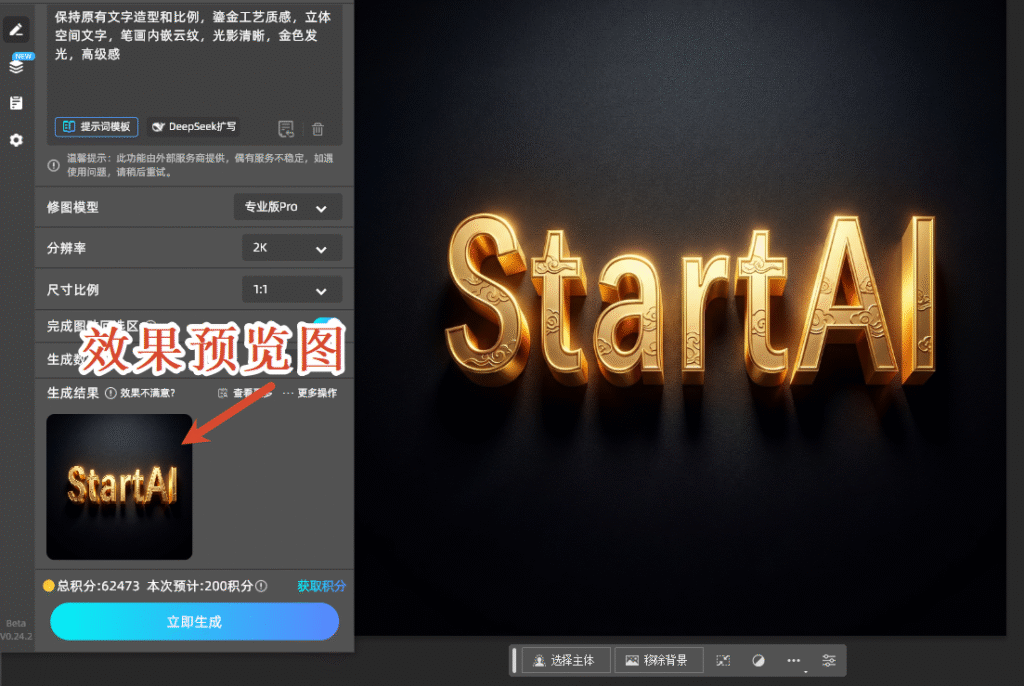
PS字体怎么做出立体感?2种方法新手也能做专业立体字
在Photoshop(简称PS)设计中,立体字体是提升作品视觉冲击力的核心技巧,广泛应用于海报设计、logo制作、电商主图、公众号封面等场景,既能让文字摆脱扁平感,又能增强画面层次感与高级感。很多新手疑惑ps字体怎么做出立体感,其实无论是纯PS原生操作,还是借助AI插件辅助,都有清晰可落地的方法,下面结合实操步骤,详细讲解两种主流方式,兼顾专业性与实用性,新手也能快速上手,同时分享ps立体字体制作的实用技巧,帮助大家高效出片。
一、PS原生操作:图层样式打造立体字体
PS原生操作无需借助任何插件,通过自带的图层样式,就能做出自然逼真的立体效果,适合所有PS版本(包括CC2015及以上),也是ps立体字体制作的基础方法,新手可先从这种方式入手,熟练掌握后再尝试进阶玩法。以下是详细实操步骤,全程无复杂操作,配合参数建议,避免反复调试。
1. 前期准备:奠定立体基础
打开PS软件,新建画布(建议尺寸1920×1080,适配大多数设计场景,可根据实际需求调整),背景色可选择纯色、渐变或纹理,建议背景与文字颜色有明显反差,更能凸显立体效果。
新建画布
选择「横排文字工具」(快捷键T),输入需要制作立体效果的文字,字体优先选择粗体(如思源黑体、Impact、阿里巴巴普惠体),粗体更易呈现立体厚度,避免选择过细字体,否则立体效果不明显——这也是ps字体立体感不突出的常见解决技巧之一。
输入文字后,调整字体大小、位置,确保文字在画布中居中或符合设计布局,选中文字图层,准备添加图层样式。
2. 核心操作:图层样式参数设置
选中文字图层,双击图层空白处,弹出「图层样式」面板,重点设置5个核心选项(斜面和浮雕、投影、内阴影、渐变叠加、描边),这是ps字体做出立体感的关键,每个参数都有明确的作用,可根据文字大小和设计需求微调,以下是通用适配参数,新手可直接套用。
图层样式面板
(1)斜面和浮雕:打造立体厚度
斜面和浮雕是立体字体的核心,主要作用是模拟文字的凸起或凹陷效果,营造基础厚度。
参数设置如下:样式选择「内斜面」,方法选择「平滑」,深度120%(可根据文字大小调整,文字越大,深度可适当增加),方向「上」,大小8-15像素,柔化1-3像素,高度60°,光泽等高线默认即可。
斜面和浮雕参数
小技巧:点击等高线图标,可切换不同高光分布,让立体字的边缘更有质感,这是提升ps立体字体高级感的小细节,很多新手容易忽略。
(2)投影:增强空间感
投影能让文字“站起来”,摆脱画布的扁平感,模拟真实光影下的阴影效果,让立体感更自然。
参数设置:混合模式选「正片叠底」,颜色选黑色或深灰色,不透明度30%-40%(避免过浓显得脏,过淡无效果),角度120°(模拟左上光源,符合人眼视觉习惯),距离12-20像素,扩展0,大小10-20像素。
投影参数
(3)内阴影:提升真实度
内阴影可让文字边缘产生内凹感,像雕刻进去一样,与投影搭配使用,能让立体字的空间感翻倍。
参数设置:混合模式「正片叠底」,颜色选深灰或深蓝,不透明度25%-35%,角度120°(与投影角度一致,保证光源统一),距离4-8像素,阻塞0,大小6-12像素。
内阴影参数
(4)渐变叠加:丰富光影层次
单纯的纯色文字立体效果较单调,渐变叠加能让文字呈现自然的光影过渡,避免死板。
参数设置:混合模式「正常」,不透明度100%,渐变选择同色系浅深搭配(如浅蓝→深蓝、浅灰→深灰,新手最稳妥的选择),样式「线性」,角度90°或120°,比例100%。
渐变叠加参数
(5)描边:强化边缘质感
描边能让立体字的边缘更清晰、更挺括,避免立体效果模糊。
参数设置:大小2-4像素,位置「外部」,颜色选深色或与渐变呼应的颜色,新手可直接选文字本身的深色系,避免颜色过于跳跃,描边不用太粗,否则会掩盖立体字的厚度。
描边参数
3. 细节优化:让立体效果更精致
完成上述图层样式设置后,可进行简单细节优化:选中文字图层,按Ctrl+J复制图层,隐藏复制图层的图层样式,将文字颜色调整为浅色(与渐变叠加的浅色一致),轻微移动2-3像素,作为立体字的高光,进一步增强层次感;
若想让立体字更有质感,可添加「图案叠加」,选择纹理素材,模拟金属、石材等材质,这也是ps立体字体进阶制作的常用技巧。
此外,若需要批量制作立体字,可右键文字图层,点击「复制图层样式」,再粘贴到新的文字图层,一键套用,节省时间,适合电商主图批量制作、海报批量排版等场景——这也是ps批量制作立体字体的高效方法。
二、高效进阶:StartAI插件制作立体字体(省时神器)
对于新手或需要高效出图的设计师而言,纯PS原生操作需要手动调整多个参数,耗时较长,而借助StartAI插件,无需反复调试参数,1分钟就能生成专业质感的立体字体,完美适配PS全版本(CC2015到2026,正版、破解版都能用),既能提升效率,又能保证效果精致,是ps立体字体制作的高效解决方案,尤其适合批量制作、追求高级质感的场景。
2. StartAI插件制作立体字体实操步骤
StartAI插件的「Banana修图」功能,是制作立体字体的核心,操作简单,零参数门槛,新手也能快速上手,具体步骤如下:
第一步:在PS中完成基础文字设置,新建画布,输入文字,调整字体、大小和位置,与原生操作的前期准备一致,无需添加任何图层样式。
第二步:调出StartAI插件面板,找到「Banana修图」功能并打开,加载做好的文字图层。
Banana修图
第三步:输入提示词生成立体效果,新手可直接套用万能提示词公式:「字体风格/材质+3D渲染+光影描述+背景氛围+画质要求」。
例如想做鎏金立体字,可输入“保持原有文字造型和比例,鎏金工艺质感,立体空间文字,笔画内嵌云纹,光影清晰,金色发光,高级感”。
填写提示词
若有参考图片,可直接上传参考图,提示词填写“将当前文字生成参考图的立体字效果”,点击「立即生成」,1分钟内即可出图。
Banana修图效果预览图
第四步:微调优化,生成立体字后,可结合PS原生操作(如添加描边、调整颜色、修改光影)进行微调,既能享受插件的高效,又能保留手动调整的灵活性,适配不同的设计需求。
三、ps立体字体制作常见技巧与注意事项
无论是原生操作还是借助StartAI插件,掌握以下技巧,能让立体字体效果更出色,同时避免常见问题,这也是ps字体做出立体感的关键补充,适合所有设计场景。
1. 字体选择:优先选择粗体、黑体,避免过细字体,粗体更能凸显立体厚度,若需使用细体,可适当增加斜面和浮雕的深度,弥补立体感不足的问题;
2. 光影统一:所有图层样式的光源角度需保持一致(建议120°),避免光影混乱,让立体效果更自然,这是ps立体字体真实感的核心;
3. 颜色搭配:立体字的颜色的选择需与背景呼应,同色系搭配更稳妥,对比色搭配更醒目,避免颜色过于杂乱,影响立体效果的呈现;
4. 适度克制:不要过度叠加图层样式,投影、斜面、渐变一股脑全加上,参数拉满,反而会让立体字显得臃肿、杂乱,适度留白,克制叠加,才是高级感的关键;
5. 场景适配:不同场景的立体字需求不同,电商主图的立体字需醒目、简洁,海报的立体字可更有设计感,logo的立体字需简洁、有辨识度,可根据场景调整效果。
四、总结
ps字体做出立体感,核心是掌握「光影与厚度」的搭配,纯PS原生操作适合新手练习基础,通过图层样式的合理设置,就能做出自然的立体效果,适合追求手动控制、细节打磨的场景;而StartAI插件则适合新手快速上手和设计师高效出图,零参数门槛、省时高效,还能做出更精致的立体效果,两种方法可结合使用,既能练习基础操作,又能提升设计效率。